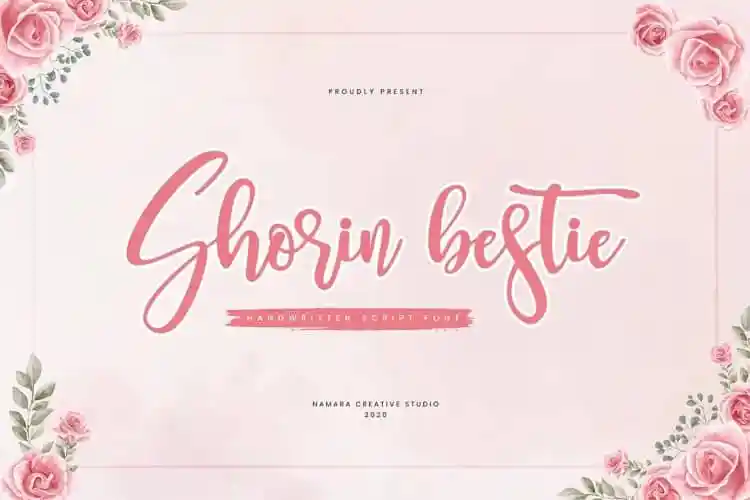
Shorin Bestie Calligraphy Font – Download Grátis
A Shorin Bestie Calligraphy Font é uma elegante e moderna fonte escrita a mão que traz um toque chic único, complementando qualquer design com facilidade. Ideal para aqueles buscando um pouco mais de personalização sem deixar de lado o charme do grafismo tradicional, essa fonte vem completa com uma gama de caracteres puros (PUA), permitindo uma manipulação intuitiva e fluida. Perfeita para designers que valorizam a simplicidade e modernidade ao mesmo tempo, esta fonte é uma ótima adição para qualquer projeto gráfico, seja para criações digitais ou impressas.